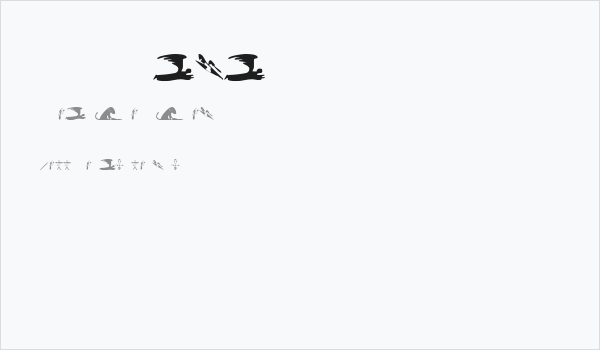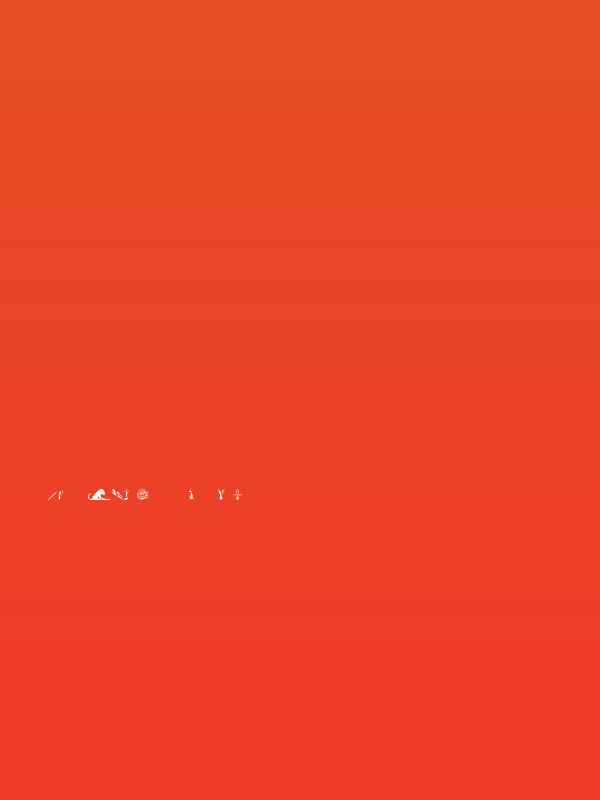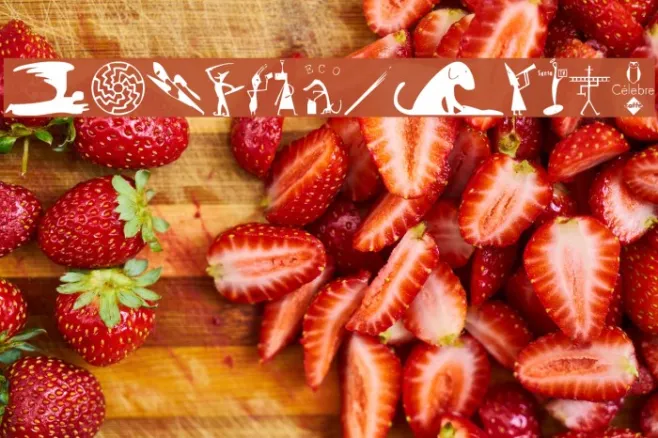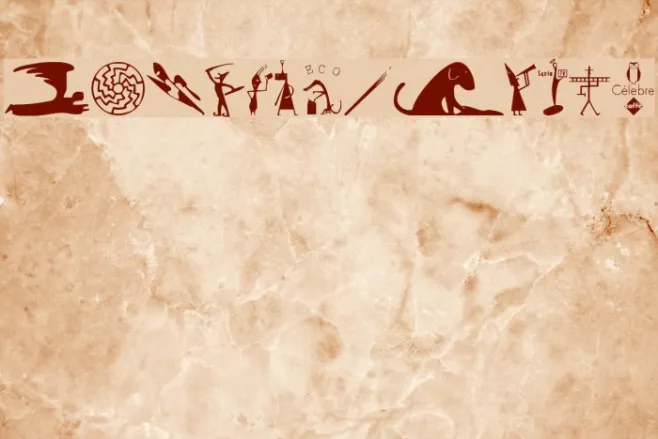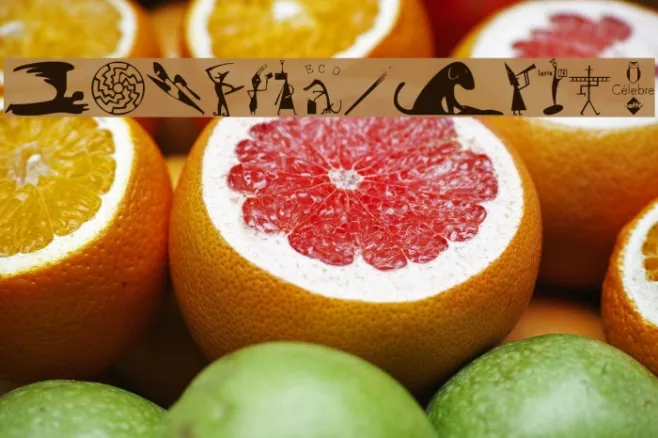
Guto Lacaz PW Font
✎ Dingbats
| Cas d'utilisation | Logos, Posters, Art Projects |
| Projets proposés | Ideal for creative projects such as art installations, posters, album covers, or any design work that benefits from a playful and artistic flair. |